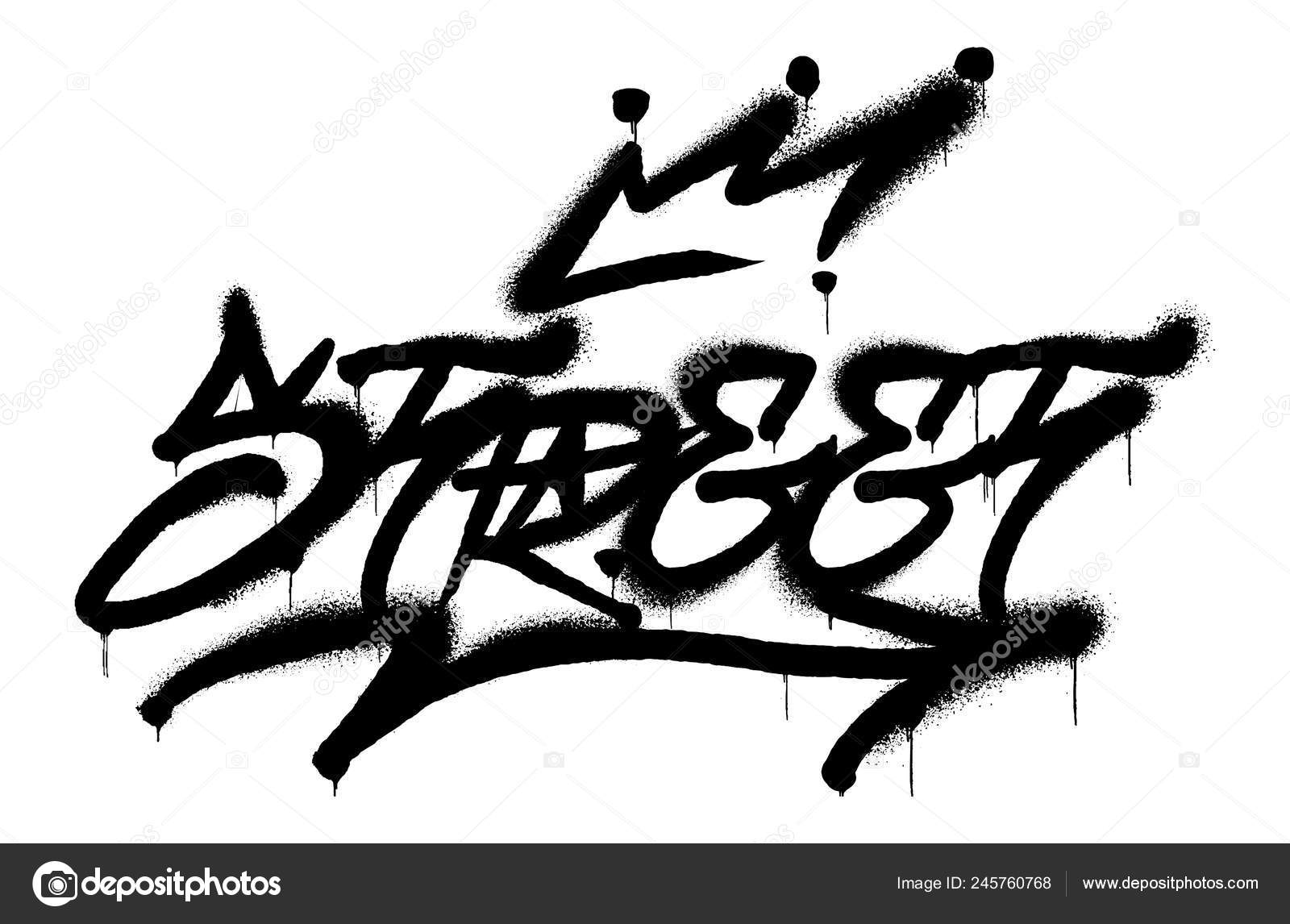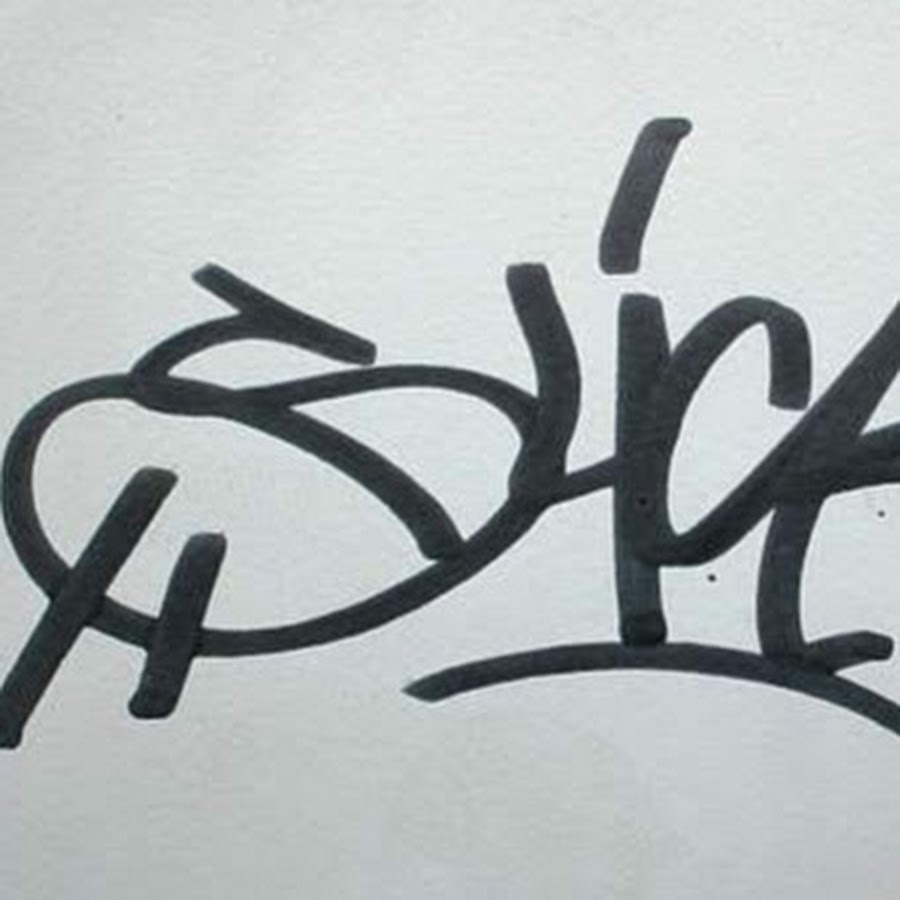
знакомимся с культурой улиц онлайн
Сегодня можно смело сказать: граффити стало искусством. Рисунки на стенах все чаще превращаются в шедевры. Темы разные: от зарисовок летних дней до памяти о великих победах и людях. «Путеводитель по Подмосковью» предлагает онлайн-прогулку по улицам Подмосковья, где можно посмотреть на работы граффитистов
Новая жизнь Трехгорки
В микрорайоне Трехгорка в подмосковном Одинцове в 2019 году прошел мировой конкурс граффити «Культурный код». Именно здесь организаторы нашли более 30 домов с глухими фасадами — лучшими холстами для рисунков. Общая площадь рисунков составила 38 тысяч квадратных метров, на эту работу потратили свыше 25 тысяч литров краски. Можете представить себе размах? Теперь Трехгорка — настоящий музей граффити под открытым небом.
Главным шедевром фестиваля стал портрет Юрия Гагарина в исполнении итальянца Йорита Агоча. Это не только самое большое изображение первого космонавта в мире, но и самое необычное — на стене 60-метрового жилого дома нарисована половина лица знаменитого русского космонавта с двумя красными полосами.
Еще одним хитом Одинцово стало изображение возлюбленной художника-сюрреалиста Весода Бреро. На одном из домов по Кутузовской улице он изобразил ее в трех ракурсах: у окна, на лестничной площадке и на фоне заката.
Есть надежда, что граффити сохранятся на долгие годы, ведь перед началом работ фасады домов обработали специальным составом.
Тем временем в Серпухове
Внимания достойны работы не только именитых художников, но и тех, кто заботится об облике своего города и старается его разнообразить. А таких людей в Подмосковье достаточно. Так, например, каждый год в Серпухове появляются новые работы граффитистов. Самая большая городская картина — павлин — появилась в 2018 году на улице Ворошилова. Гордая птица изображена на фоне храма Илии Пророка и олицетворяет символ Серпухова.
С инициативой о создании масштабного граффити выступил глава города.
Главным героем другого уличного изображения стал серпуховский князь Владимир Храбрый. Он занимает центральную часть композиции «Воины эпох», за его спиной — фрагменты важных исторических событий: Куликовской битвы, Отечественной войны и Великой Отечественной войны.
Кроме того, вот уже больше года одну из центральных улиц города — Советскую — украшают граффити, выполненные в стилистике плакатов СССР. Одна из работ посвящена ключевым видам серпуховской продукции: здесь нашли место и железобетонные изделия, и текстиль, и даже автозапчасти. А на соседнем доме — призыв к активному образу жизни. Граффити называется «Спорт — это жизнь» и состоит из зарисовок с разными видами спорта: от стрельбы до бега.
Рошаль героический
Другой уголок Подмосковья, где граффити стали частью городского ансамбля, — Рошаль. Здесь накануне 9 Мая в 2019 году художники расписали три здания.
С фасадов домов на жителей города теперь смотрят Герои Великой Отечественной войны.
Портрет маршала СССР, дважды Героя Советского Союза Ивана Конева появился на фасаде дома № 19 на улице Советской. Портреты Героев Советского Союза, почетных граждан Рошаля Николая Кочеткова и Вениамина Гусева поместили на фасадах домов № 24а на улице Свердлова и № 4 на улице Карла Либкнехта. Серьезная работа началась еще до написания картин. Нужно было проработать эскизы так, чтобы портреты гармонично встроились в облик главных улиц города. Архитекторы и художники остановились на эффекте сепии, чтобы фасады выглядели как фотографии военного времени.
В Рошале ежегодно проводится арт-фестиваль «Город-сад», в рамках которого уличные художники вдыхают новые краски в привычные городские пейзажи. Фасады жилых домов украшают яркие зарисовки, которые поднимают настроение зимой.
Граффити Подольска и Бронниц
В середине августа 2019 года в подмосковном Подольске художники завершили работу над граффити с изображением Героя Советского Союза Виктора Талалихина.
А в Бронницах неожиданно поселился Лионель Месси. Художники создали этот портрет, потому что футболист останавливался на чемпионате мира в Бронницах и у него в этих числах был день рождения. Вышло симпатично, согласны?
Последний раз Таки 183 был владельцем мастерской по ремонту иномарок. В интервью New York Daily News от 9 апреля 1989 года он рассказал о своем выходе на пенсию в качестве автора граффити: «Как только я занялся чем-то более продуктивным в моей жизни, я бросил. В конце концов я занялся бизнесом, женился. , купил дом, завел ребенка Не купил универсал, но я вырос, можно так сказать.»